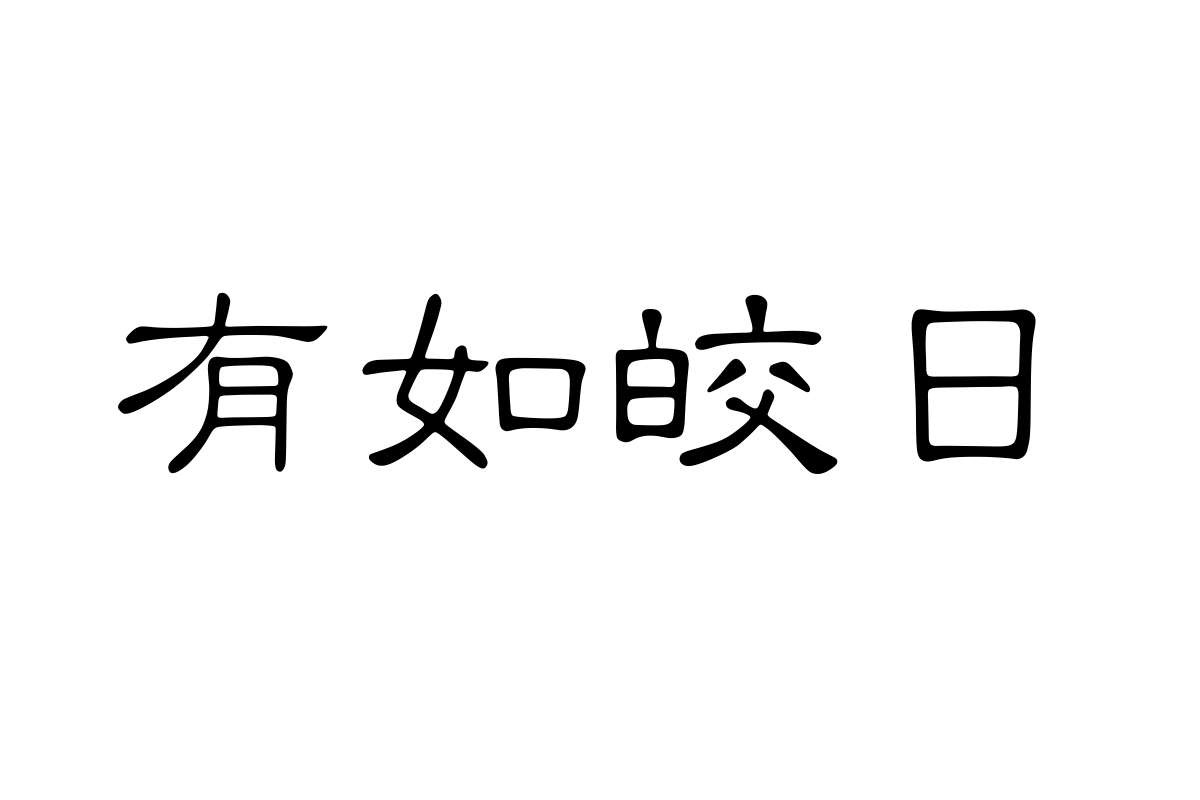
汉仪小隶书简是一款具有现代感和传统韵味的字体。它结合了现代设计元素和传统的书法艺术,创造出独特的字体风格。这款字体适用于各种设计场景,如广告、海报、包装等。
汉仪小隶书简的特点如下:
1. 字形结构:字体采用简洁的线条和笔画,形成一种流畅而有力的视觉效果。字形紧凑,易于阅读和辨识。
2. 字体风格:这款字体既有现代设计的简洁性,又保留了传统书法的艺术美感。它的线条流畅,笔触自然,给人一种优雅而庄重的感觉。
3. 适用范围:汉仪小隶书简适用于各种设计领域,包括广告、海报、包装、网页等。它能够很好地融入各种设计风格中,为设计作品增添独特的魅力。
4. 可定制性:汉仪小隶书简支持个性化定制,用户可以根据自己的需求调整字体的粗细、间距、倾斜度等参数,以适应不同的设计需求。
总之,汉仪小隶书简是一款兼具现代感和传统韵味的字体,适用于各种设计场景,能够满足设计师们对于字体风格的需求。